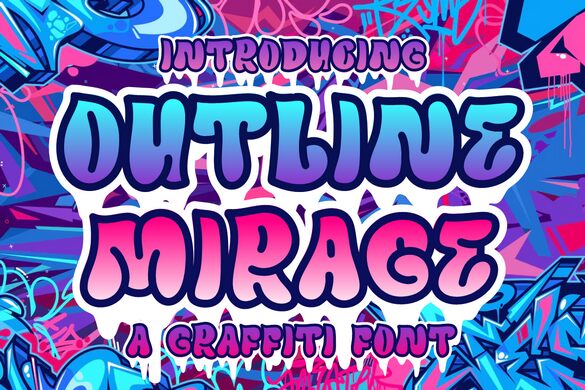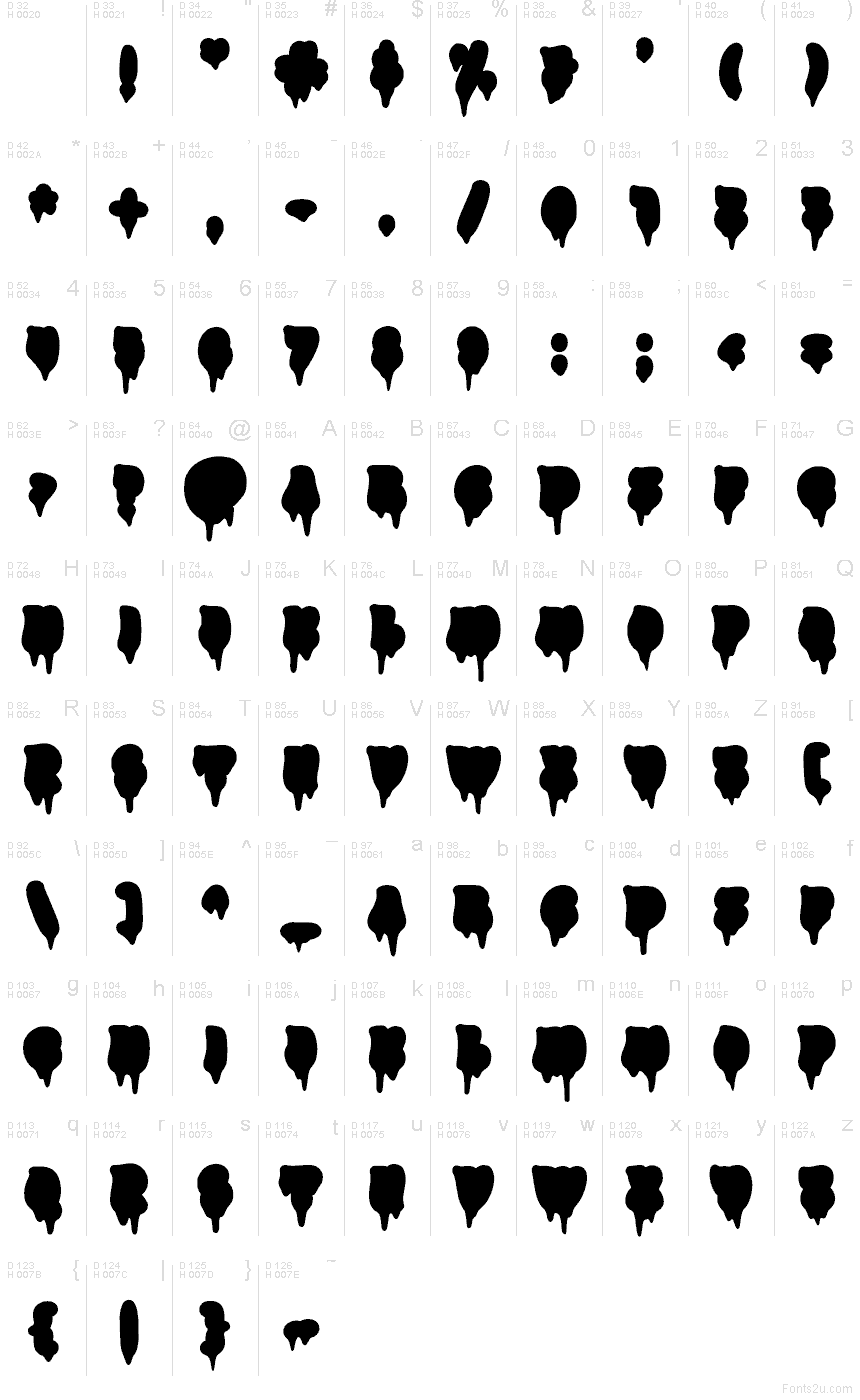
Outline Mirage Melt
Outline Mirage Melt od Shanaf Studio je bezplatné graffiti písmo so vzhľadom farby, ktorá sa rozpúšťa a steká po stene. Písmená pôsobia masívne a komiksovo, so zaoblenými tvarmi a dlhými kvapkami, ktoré menia celú abecedu na temnú, sirupovitú siluetu.
Ideálne na plagáty, streetwearové značky, hudobné obaly, halloweenske letáky alebo titulky, kde vynikne „roztečený“ štýl viac ako čisté písmo. Používajte ho v krátkych slovách, logách alebo výrazných nadpisoch, pretože stékajúce tvary a nahromadené konce písmen tvoria hlavný vizuálny dojem.